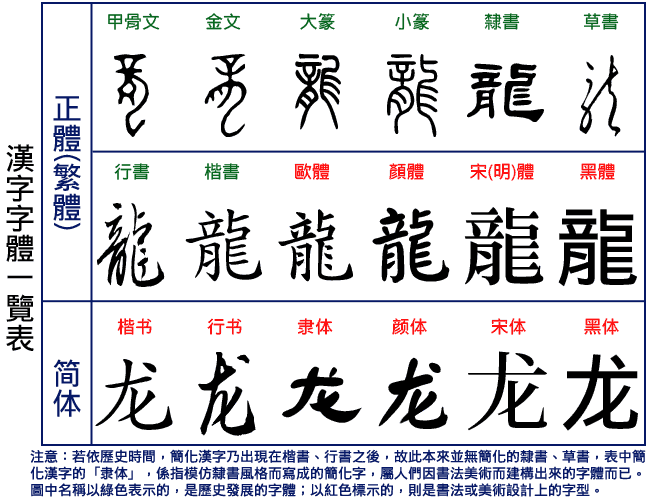
汉字
导语汉字,是汉字文化圈内使用甚广的一种文字,属于表意文字书写系统的词素音节文字。汉字为上古时代的中国人所创制,信史可追溯至约公元前1300年商朝的甲骨文。汉字在古代已发展至高度完备的水平,不止中国使用(中文),更在很长时期内充当东亚地区唯一的国际文字,二
汉字,是汉字文化圈内使用甚广的一种文字,属于表意文字书写系统的词素音节文字。汉字为上古时代的中国人所创制,信史可追溯至约公元前1300年商朝的甲骨文。汉字在古代已发展至高度完备的水平,不止中国使用(中文),更在很长时期内充当东亚地区唯一的国际文字,二十世纪前还是日本、朝鲜半岛、越南等东亚和东南亚国家官方的书面规范文字。
现代汉字,在中文体系大致分成正体中文与简体中文两个体系。前者主要用于台湾(俗称繁体中文)与港澳地区以及欧洲和北美的华人圈与八十年代以前的新加坡、马来西亚,而后者主要用于中国大陆、东南亚的华人以及八十年代之后的新加坡、马来西亚,一般来讲,两个体系的使用者都能看懂另一体系的文字。日本和韩国则是另行各自制定了官方的汉字使用规范,但汉字在越南和朝鲜已不再具有官方规范地位。
深绿色:正式或绝大多数文书使用正体字的地区(台湾与港、澳地区)。
绿色:正式采用简体字,但正体字仍常用的地区(马来西亚、新加坡)。
青绿色:正式使用简体字而鲜少使用正体字的地区(中国大陆)。
浅绿色:官方语文中有使用汉字且沿用至今的地区(日本、韩国)。
浅黄色:曾在官方语文中使用汉字,但现今不用的地区(越南、朝鲜、蒙古)。
字源
汉字一词早出自《北史》卷九本纪第九,“章宗一”:“十八年,封金源郡王。始习本朝语言小字,及汉字经书,以进士完颜匡、司经徐孝美等侍读”。
《金史》也出现多次,如:“女真初无文字,及破辽,获契丹、汉人,始通契丹、汉字,于是诸子皆学之”。 “长子布辉,识女真、契丹、汉字,善骑射”。
在清朝前期,政府官方文字是满文,当时已用汉字一词称呼中国传统的文字。更之前的古代中国,因为没有与他国区分的必要,多称呼为“字”或“文字”。
直到目前为止,台湾官方文字相关政策制定的中华民国教育部,以定义官方文字的“国字”作为称谓,而不使用其他国家使用的汉字一词,例如《国字标准字形表》等。民进党执政时期曾有意更名“汉字”,但遭媒体及部份人士批评为“去中国化”的一环而作罢。
另外,日本人也称呼为“汉字”,以别于由汉字衍生的假名。在南韩,汉字则与训民正音(谚文)相区别。
汉字的特点
汉字的特点有以下几项:
字根组字:以本身即有意义的869个声母及265个形母的象形、指事字为最基本字根部件,称为“字源”,通常为独体字,例如“日”、“月”,可组成各种复合部件(如“明”,可再堆栈组合成汉字盟、萌、曌等字)、以及一般认知的字(“明”本身就是一个字)。
表意:承上,字根本身表义,多个字根合成新义,且空间的配置对字义有影响。(朱邦复先生的字易即是探讨此)
相容并蓄:各语言、各领域应用可以六书基本规则,可贴近自身领域、地域所需组出所需要之字。
书同文:汉字本身不完全表音,不同方言、甚至语言,仍可书同文,以文意、字义来互相了解。
独有的文化如对联、书法艺术等。
汉字字形史
甲骨文汉字是世界上最古老的三大文字系统之一。其中,古埃及的圣书字、两河流域苏美尔人的楔形文字已经失传,仅有中国的汉字沿用至今。
图:甲骨文
传说中,汉字起源于仓颉造字。黄帝的史官仓颉根据日月形状、鸟兽足印创造了汉字。从历史角度来看,复杂的汉字系统不可能由一个人发明,仓颉应该是在汉字的搜集、整理、统一上做出了突出贡献,所以《荀子‧解蔽》中记载“好书者众矣,而仓颉独传者,一也”,而汉朝淮南子一书更描述仓颉的贡献为“天雨粟,鬼夜哭”:描述文字的发明有如天上降下五谷广披大众,使得资讯透过文字能传载给任何人;而仓颉之前已去逝的人(鬼)都痛哭没有办法享用到文字的好处。
有观点认为《周易》中的八卦对汉字形成有较大影响,但支持者甚少。
1.原始文字
文字发明前的口语知识在传播和积累中有明显缺点,原始人类使用了结绳、刻契、图画的方法辅助记事,后来用特征图形来简化、取代图画。当图形符号简化到一定程度,并形成与语言的特定对应时,原始文字形成。
1994年,湖北杨家湾大溪文化遗址出土了大量陶器,其上170多种符号中,部分特征与甲骨文有较大类似之处。这一发现将原始汉字的形成过程推定到距今6000年以前。此外,山东大汶口出土的陶器上的象形符号,西安半坡彩陶上的几何符号,河南贾湖距今8000年前龟甲上的几何符号贾湖契刻符号等,都可能是原始文字形成中(或形成前)不同阶段的表现。
但是,商朝以后的汉字和这些几何符号是否一脉相承?这个问题还在争议中。许多学者提出,这些符号不一定是汉字的前身,甚至不能绝对肯定是文字符号。
2.象形指事时代
从甲骨文到小篆,汉字经历了从巨细靡遗描绘意象的方式往简化成容易纪录刻画的方向变迁,字形逐步脱离事物的具体形象。这一时期的汉字也称为古文字。
商周时期的甲骨文已经是一种比较完整的文字体系。在已发现的4500多个甲骨文单字中,目前已能认出近2000字。与甲骨文同期,青铜器上铸造的文字称为金文或钟鼎文,西周时期的《散氏盘》、《毛公鼎》具备很高的史料和艺术价值。
春秋时代开始,各地诸侯相争,而原本周文化独尊的局面逐渐破坏,各地区文化开始有"在地化"的改变趋势。到了战国时代以后,这种情况更明显,在文字使用方面可以粗略依照地域分为五大系统:东方齐系、东北燕系、南方楚系、北方晋系和西方秦系文字,各系统的文字大体上相近,只有小部份文字有所差异,因此彼此文书往来并没有太大问题。
秦始皇统一中国后,李斯在大篆(秦系文字)和六国古文的基础上,进行规范和整理,制定出了小篆作为秦朝的标准书写字体,统一了中国的文字。小篆呈长方形,笔画圆润流畅。
小篆解决了各国文字间出现大量异体字的情况,“书同文”的历史从此开始。文字的统一有力促进了不同语族间的文化传播,对中国的统一以及东亚各国的文化交流发挥了重要作用,为世界文字史所罕见。
汉字的发展经历了许多不同的演变。初期汉字系统的字数很少,以象形与指事的独体字为主,大量事物以通假字来表示,使文字表述存在较大歧义。例如先秦的“文”,兼有后世的新字“纹”的功能,表示一组成各种事务的规律、型式,不单指文字的文,也包含野兽身上的花“文”、布上面的织“文”、手指的指“文”等数种含意。
除了“凹”、“凸”等特例直到唐朝才发明[3],大部分的象形指事字很早就已经定型,成为下个时代形声会意组字法的基础。
3.形声会意时代
为了能更精准的表述,最早从小篆的时代开始一直到现代,因应随文明发展不断增加的新事物,以基本的象形指事字为基础,发展了形声、会意的组字法,以组合方式,来细化大量的字出来,使得文书上记载越来越精密,到今天一直为造字的主力。
例如:
最早海上的交通工具就只有:“舟”一种;但演化到现在,细分成“舨、舟、艇、船、舰”等不同小大规模与形制的“舟”。
一开始金属只有“金”一种,但随着冶金技术的发展,对于金属的知识更加丰富,“金”被细化成“金”、“银”、“铜”、“铁”等等。
隋文帝杨坚原为隨国公,但因“隨”字的“辶”有不稳定之意,故去掉“辶”,而造“隋”字作为国号。
唐朝和武周时,武则天根据“日月当空”之意而造字“曌”(同“照”字)作为她的名字。同时发明的文字还包括圀、瞾、囝等。人称则天文字。
五代刘龑取“飞龙在天”之意创了自己名字内的“䶮”字。
在近代,由于大量西方知识的涌入,也造了许多字。例如随着“Beer”传入中国,如何用汉字表达是一个问题,最初译为皮酒,后觉不妥,于1910年左右创造了“啤”字——译为“啤酒”。(而在同一时期,朝鲜半岛与日本采用了“麦酒”这个名字作为“啤酒”的译名。)
近代化学名词在翻译成中文时,也用了形声会意造字法,造了一系列的新字,例如“溴”、“钚”元素与“醇”基、“醛”基等有机化合物名词。另外化学上还有很多将两个字的部分凑合起来表示新的意义的字,其发音也是两字发音凑合而来。如“烃”(碳氢)、“羰”(碳氧)、“巯”(氢硫)、“羟”(氢氧)等。
为了表示英制的单位,还造了一些多音节的字,如浬(海里)、嗧(加仑)、瓩(千瓦)、呎(英尺)、哩(英里)等度量衡用字。目前在台湾仍然使用,但多为单多音节混用,港澳地区亦同。不过这些多音节的字在1977年7月20日大陆的中国文字改革委员会和国家标准计量局所发的《关于部分计量单位名称统一用字的通知》中被淘汰,在大陆地区不使用。
有了造好的象形、指事的独体字为基础,使用形声、会意组字法随着文明的发展,组出表示新事物的合体字,这使得记载为文时,以前述的各种不同的船来说,只要看一单位的字形,我们就知道指的是那一种“舟”,这样辨识理解的效率非常高;反过来,以组词的方式就要看过前后文(或短或长)有其他哪些字才能判断正确的意义,较缺乏辨识效率,但方便口语沟通(汉字同音字太多,听觉不易辨识,解法一为组词,二为如韩日语数音为一字:“浬”发音为海里)。
汉字字体史
小篆笔画以曲线为主,后来逐步变得直线特征较多、更容易书写。到汉代,隶书取代小篆成为主要书体。隶书的出现,奠定了现代汉字字形结构的基础,成为古今文字的分水岭。
汉代以后,汉字的书写方式逐步从木简和竹简,发展到到在帛、纸上的毛笔书写。草书、楷书、行书等字体开始出艺术。古代印刷术发明后,出现了用于印刷的新字形宋体,传入日本,衍生出明体(可能是在明朝传入。微软操作系统默认字形,细明体即为之),在现代又陆续出现了黑体、仿宋体等字形。
图:汉字字体一览表